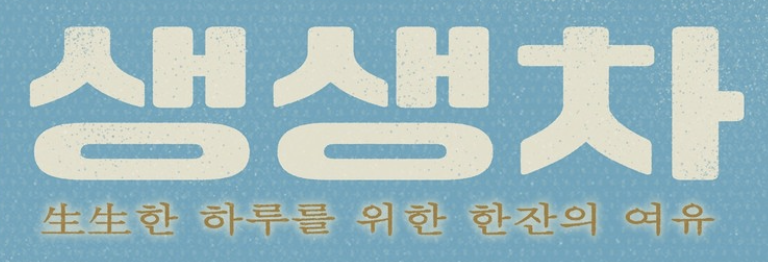
프릳츠 포스터 폰트 ain*** 2023.01.19 프릳츠 포스터에 쓰여진 서체인데 아시는 분 계시다면 알려주시면 감사하겠습니다 :) 댓글 0 등록 sta*** MBC 1961굴림 같네요. 가로폭 값을 세로폭 값보다 더 줘서 옆으로 더 납작하게 만들어 쓴 것 같네요. https://www.sandollcloud.com/font/16922.html 2023-01-20 답글 달기 댓글 더보기 쉽고 빠르게 가장 비슷한 폰트를 알고 싶다면? 이미지로 검색하기
MBC 1961굴림 같네요. 가로폭 값을 세로폭 값보다 더 줘서 옆으로 더 납작하게 만들어 쓴 것 같네요. https://www.sandollcloud.com/font/16922.html